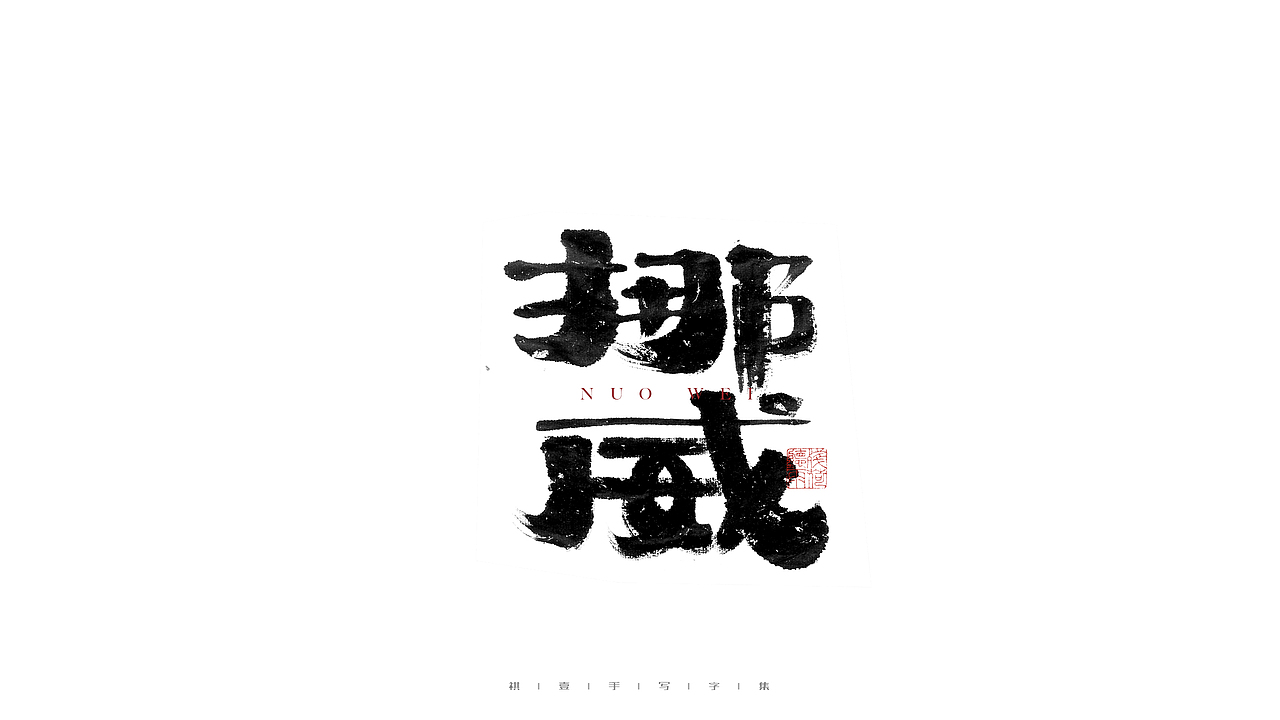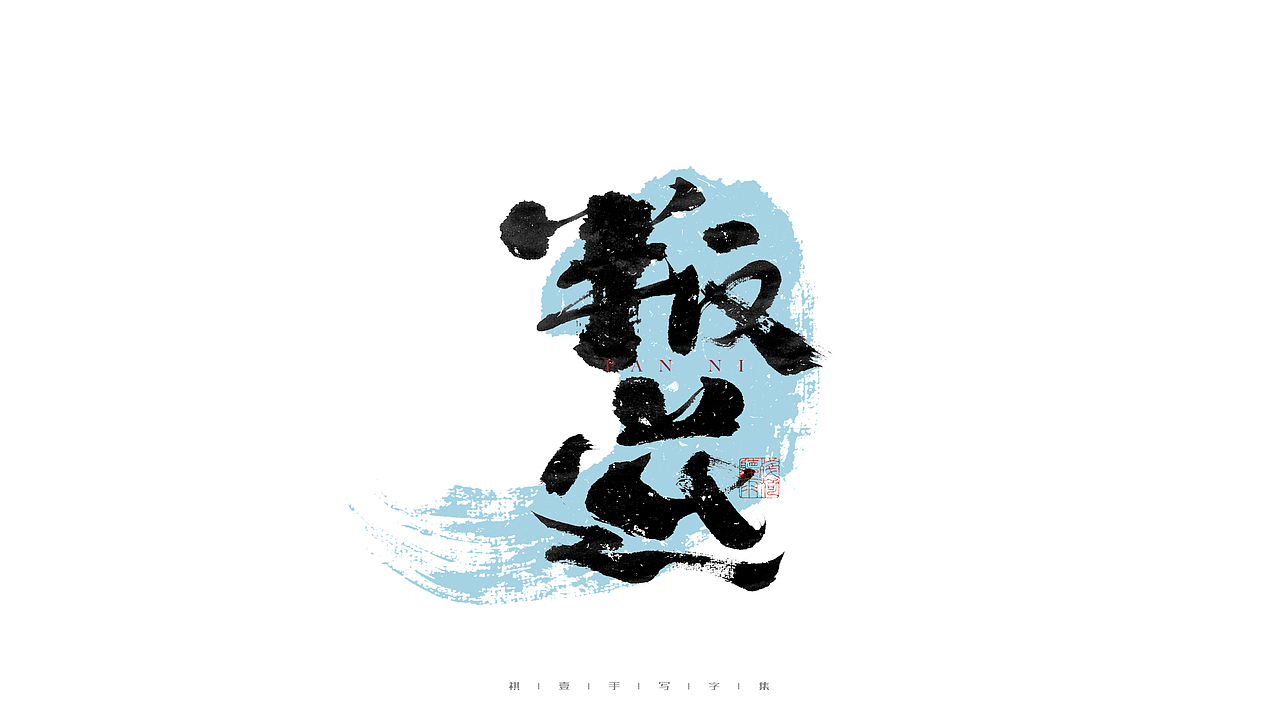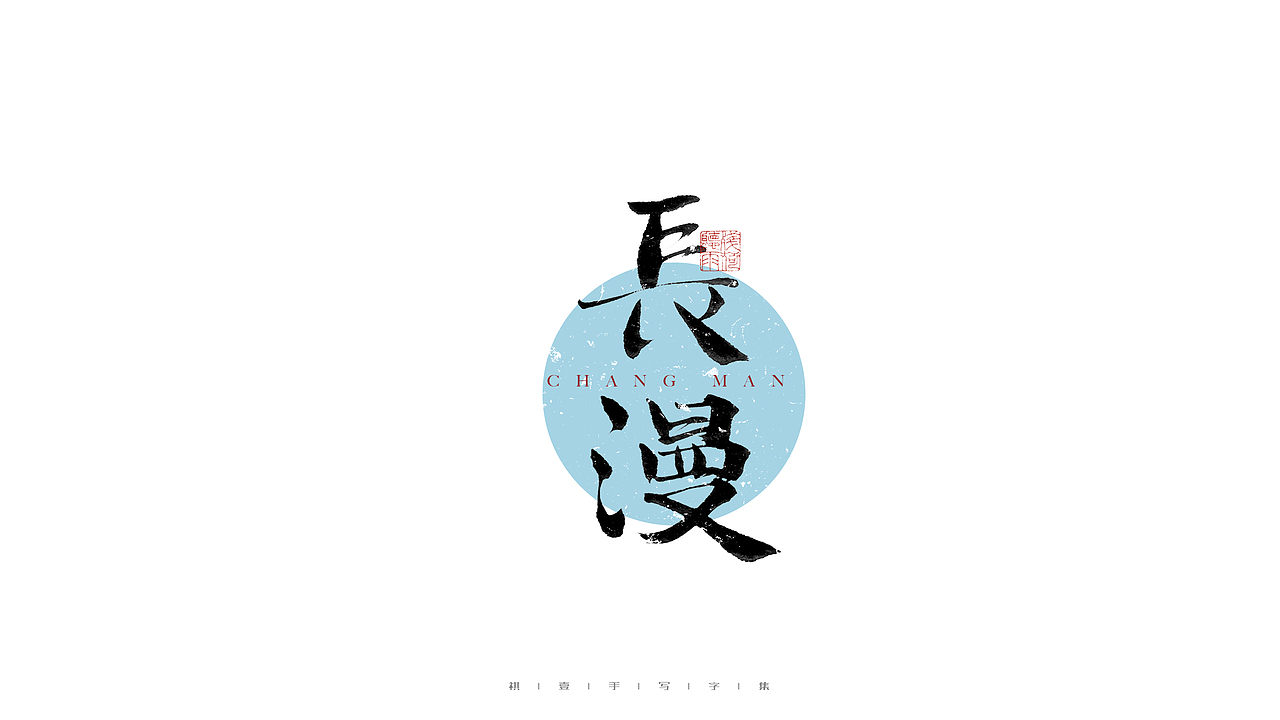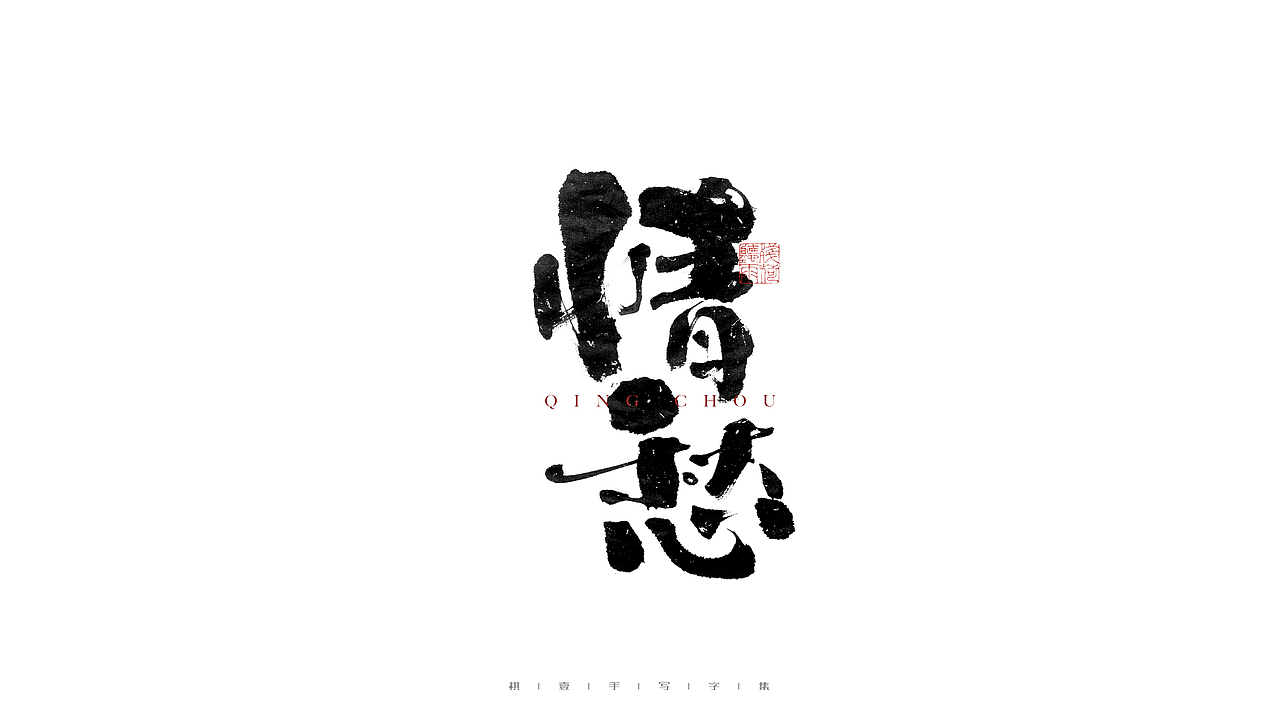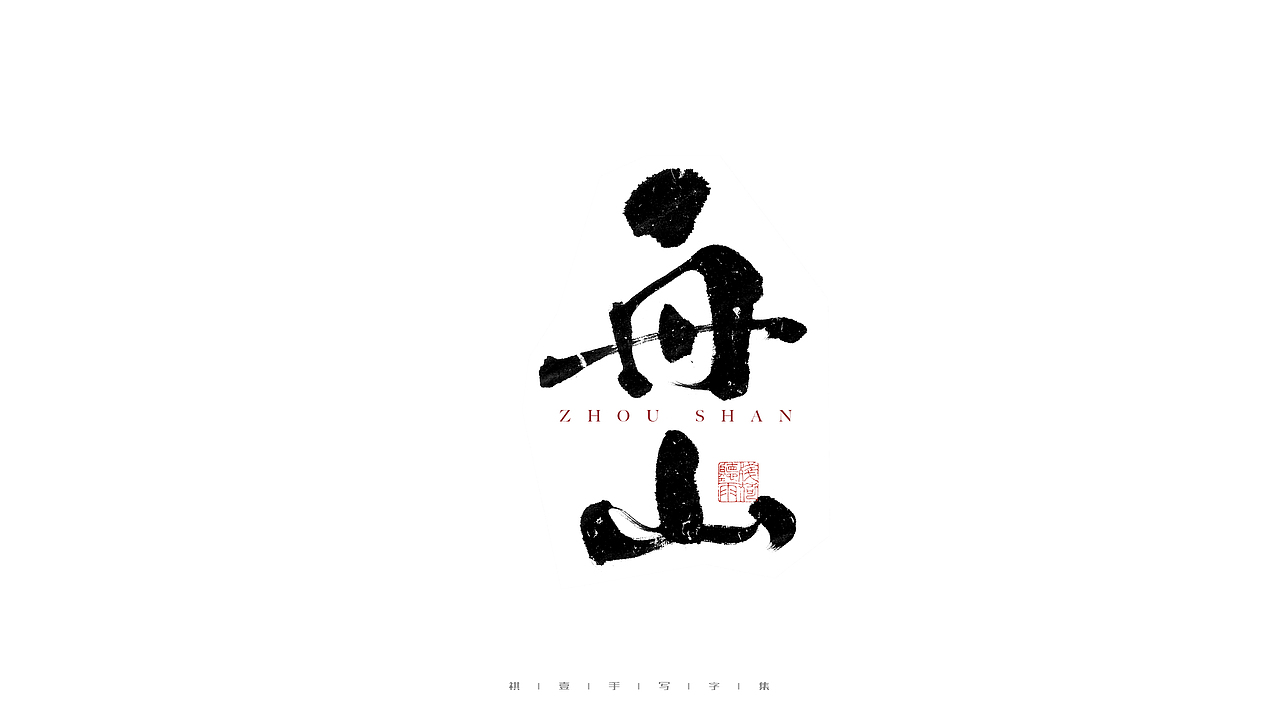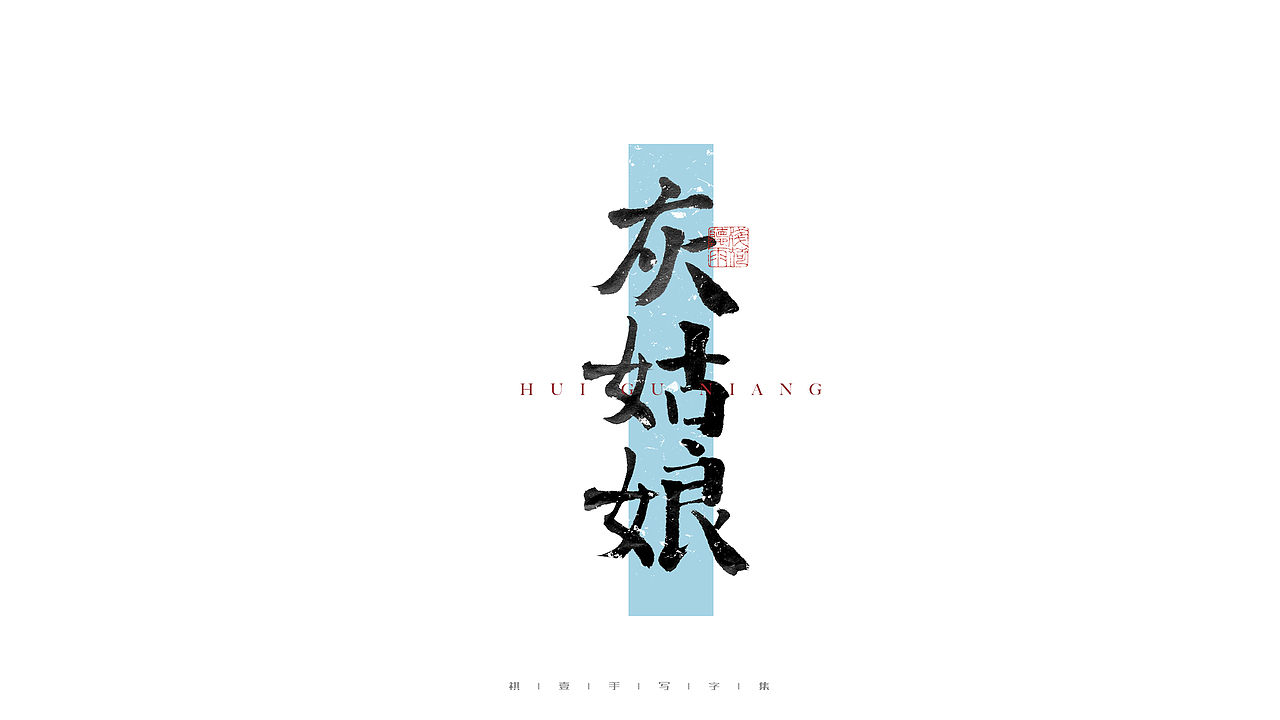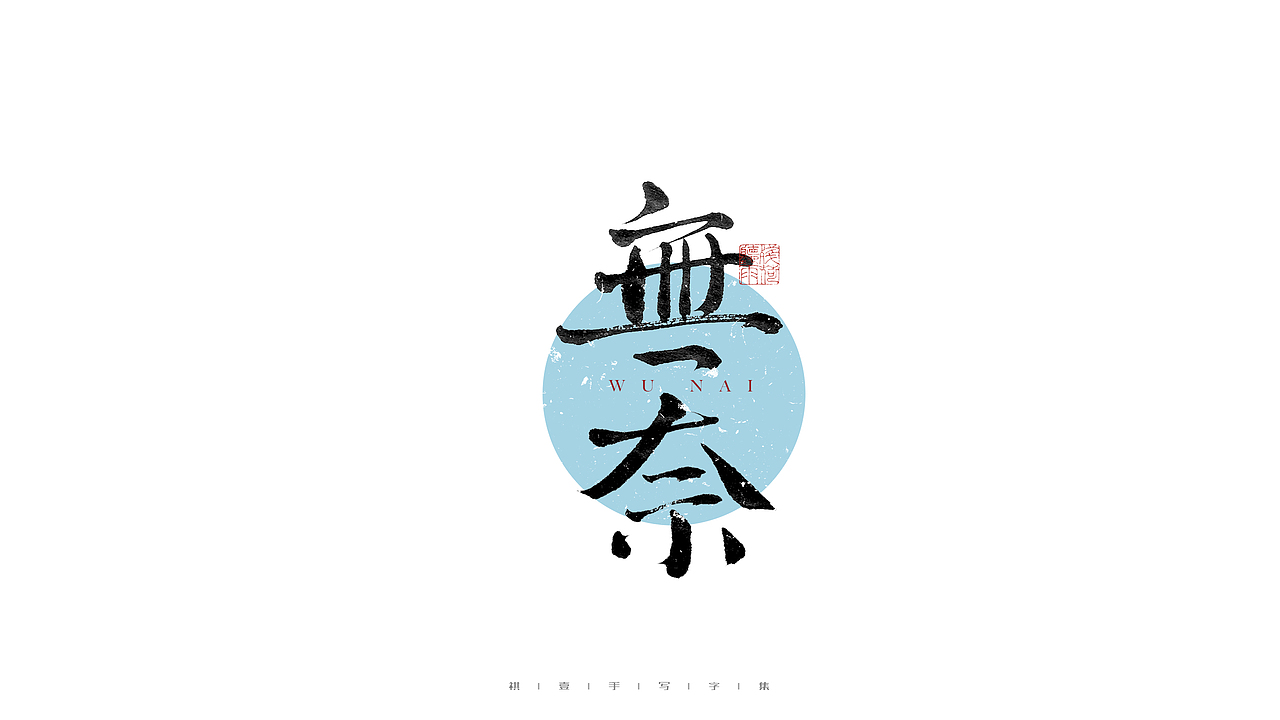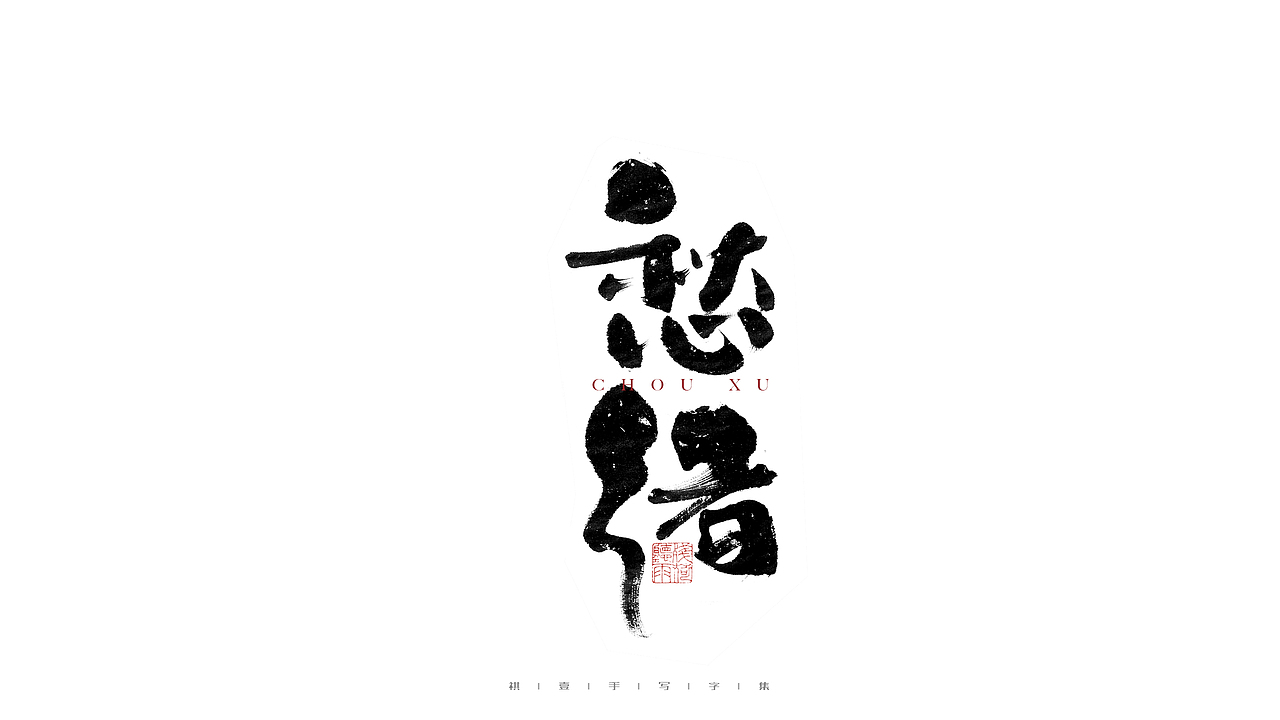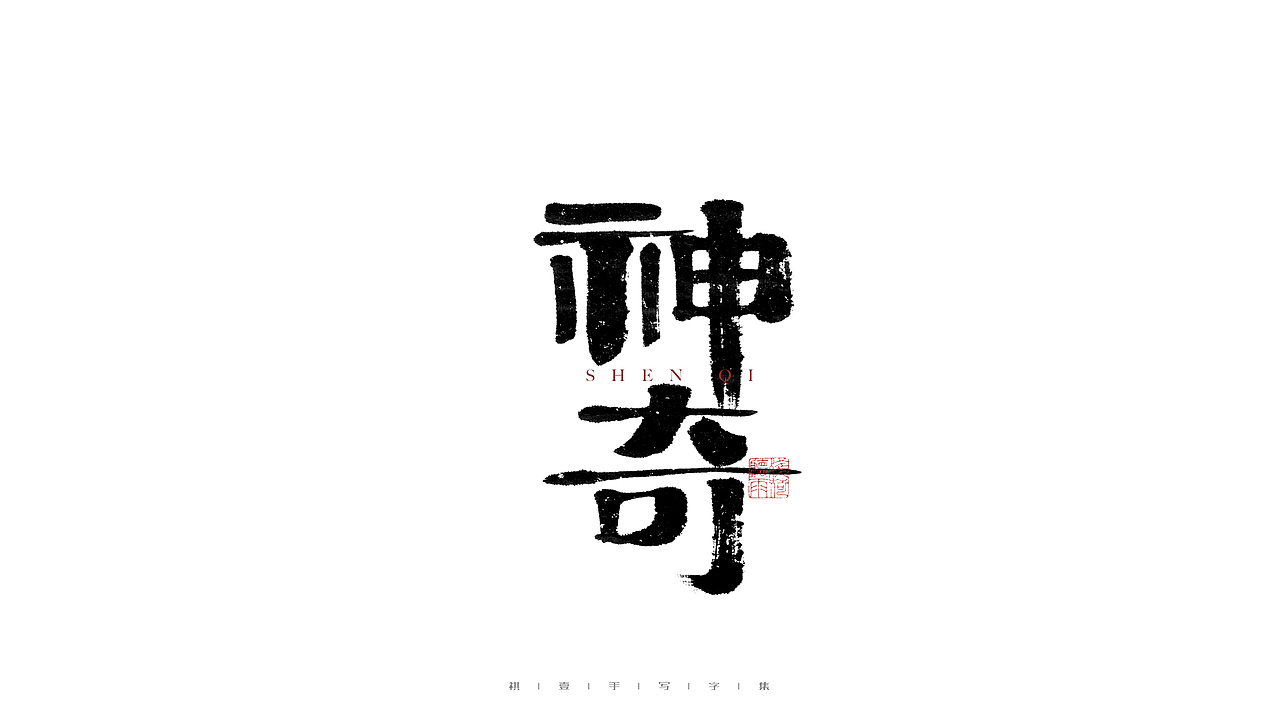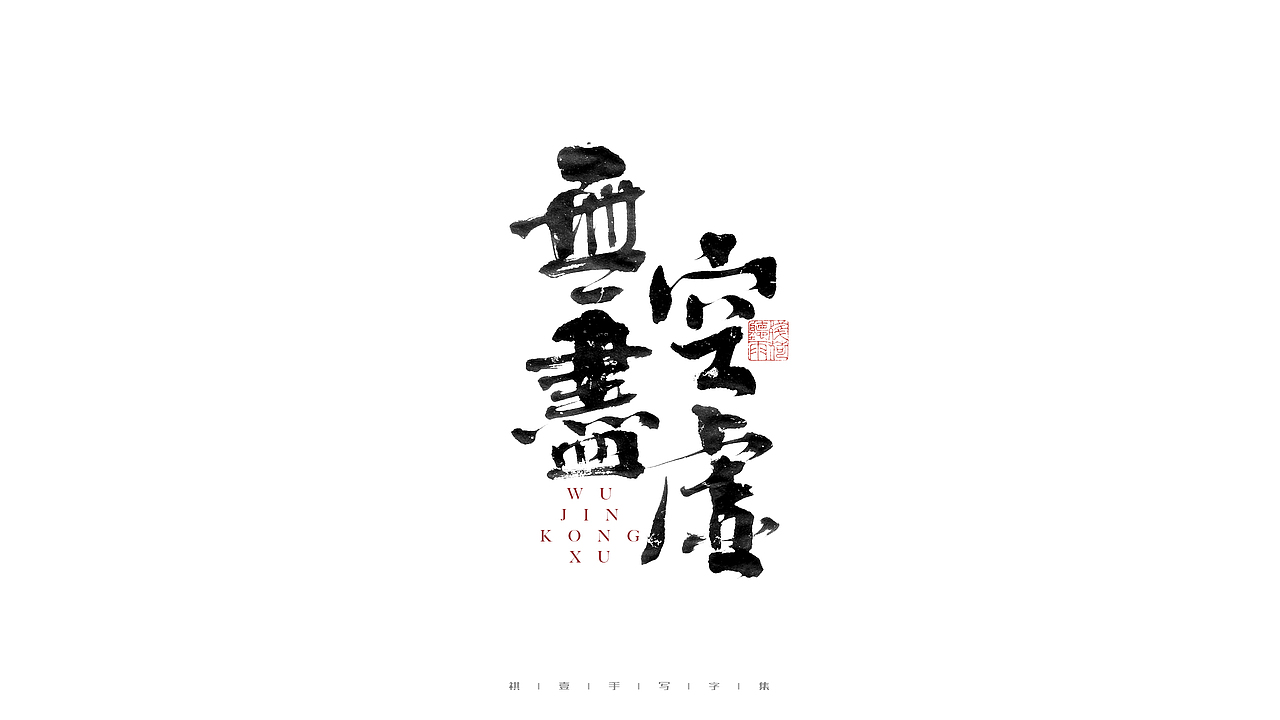
自言字语 —— 一组手写毛笔字(图ZMjc5MTAyNTcy) - 字体/字形 - 站酷设计师祺壹原创素材 - 站酷ZCOOL
自言字语 —— 一组手写毛笔字(图ZMjc5MTAyNTAw) - 字体/字形 - 站酷设计师祺壹原创素材 - 站酷ZCOOL
自言字语 —— 一组手写毛笔字(图ZMjc5MTAyNDY0) - 字体/字形 - 站酷设计师祺壹原创素材 - 站酷ZCOOL
自言字语 —— 一组手写毛笔字(图ZMjc5MTAyNTIw) - 字体/字形 - 站酷设计师祺壹原创素材 - 站酷ZCOOL
自言字语 —— 一组手写毛笔字(图ZMjc5MTAyNTA4) - 字体/字形 - 站酷设计师祺壹原创素材 - 站酷ZCOOL
自言字语 —— 一组手写毛笔字(图ZMjc5MTAyNTM2) - 字体/字形 - 站酷设计师祺壹原创素材 - 站酷ZCOOL
自言字语 —— 一组手写毛笔字(图ZMjc5MTAyNTEy) - 字体/字形 - 站酷设计师祺壹原创素材 - 站酷ZCOOL
自言字语 —— 一组手写毛笔字(图ZMjc5MTAyNTgw) - 字体/字形 - 站酷设计师祺壹原创素材 - 站酷ZCOOL
自言字语 —— 一组手写毛笔字(图ZMjc5MTAyNDgw) - 字体/字形 - 站酷设计师祺壹原创素材 - 站酷ZCOOL
自言字语 —— 一组手写毛笔字(图ZMjc5MTAyNTA0) - 字体/字形 - 站酷设计师祺壹原创素材 - 站酷ZCOOL
自言字语 —— 一组手写毛笔字(图ZMjc5MTAyNDY4) - 字体/字形 - 站酷设计师祺壹原创素材 - 站酷ZCOOL
自言字语 —— 一组手写毛笔字(图ZMjc5MTAyNTI4) - 字体/字形 - 站酷设计师祺壹原创素材 - 站酷ZCOOL
自言字语 —— 一组手写毛笔字(图ZMjc5MTAyNDYw) - 字体/字形 - 站酷设计师祺壹原创素材 - 站酷ZCOOL
自言字语 —— 一组手写毛笔字(图ZMjc5MTAyNTE2) - 字体/字形 - 站酷设计师祺壹原创素材 - 站酷ZCOOL
自言字语 —— 一组手写毛笔字(图ZMjc5MTAyNTMy) - 字体/字形 - 站酷设计师祺壹原创素材 - 站酷ZCOOL
自言字语 —— 一组手写毛笔字(图ZMjc5MTAyNDky) - 字体/字形 - 站酷设计师祺壹原创素材 - 站酷ZCOOL
自言字语 —— 一组手写毛笔字(图ZMjc5MTAyNDg0) - 字体/字形 - 站酷设计师祺壹原创素材 - 站酷ZCOOL
自言字语 —— 一组手写毛笔字(图ZMjc5MTAyNDU2) - 字体/字形 - 站酷设计师祺壹原创素材 - 站酷ZCOOL
自言字语 —— 一组手写毛笔字(图ZMjc5MTAyNDc2) - 字体/字形 - 站酷设计师祺壹原创素材 - 站酷ZCOOL
自言字语 —— 一组手写毛笔字(图ZMjc5MTAyNTQ0) - 字体/字形 - 站酷设计师祺壹原创素材 - 站酷ZCOOL
自言字语 —— 一组手写毛笔字(图ZMjc5MTAyNTI0) - 字体/字形 - 站酷设计师祺壹原创素材 - 站酷ZCOOL
自言字语 —— 一组手写毛笔字(图ZMjc5MTAyNTU2) - 字体/字形 - 站酷设计师祺壹原创素材 - 站酷ZCOOL
自言字语 —— 一组手写毛笔字(图ZMjc5MTAyNDg4) - 字体/字形 - 站酷设计师祺壹原创素材 - 站酷ZCOOL
自言字语 —— 一组手写毛笔字(图ZMjc5MTAyNDk2) - 字体/字形 - 站酷设计师祺壹原创素材 - 站酷ZCOOL
自言字语 —— 一组手写毛笔字(图ZMjc5MTAyNTQ4) - 字体/字形 - 站酷设计师祺壹原创素材 - 站酷ZCOOL
自言字语 —— 一组手写毛笔字(图ZMjc5MTAyNTUy) - 字体/字形 - 站酷设计师祺壹原创素材 - 站酷ZCOOL
自言字语 —— 一组手写毛笔字(图ZMjc5MTAyNTYw) - 字体/字形 - 站酷设计师祺壹原创素材 - 站酷ZCOOL
自言字语 —— 一组手写毛笔字(图ZMjc5MTAyNTY4) - 字体/字形 - 站酷设计师祺壹原创素材 - 站酷ZCOOL
自言字语 —— 一组手写毛笔字(图ZMjc5MTAyNDcy) - 字体/字形 - 站酷设计师祺壹原创素材 - 站酷ZCOOL
自言字语 —— 一组手写毛笔字(图ZMjc5MTAyNTc2) - 字体/字形 - 站酷设计师祺壹原创素材 - 站酷ZCOOL
自言字语 —— 一组手写毛笔字(图ZMjc5MTAyNTQw) - 字体/字形 - 站酷设计师祺壹原创素材 - 站酷ZCOOL
自言字语 —— 一组手写毛笔字(图ZMjc5MTAyNTY0) - 字体/字形 - 站酷设计师祺壹原创素材 - 站酷ZCOOL